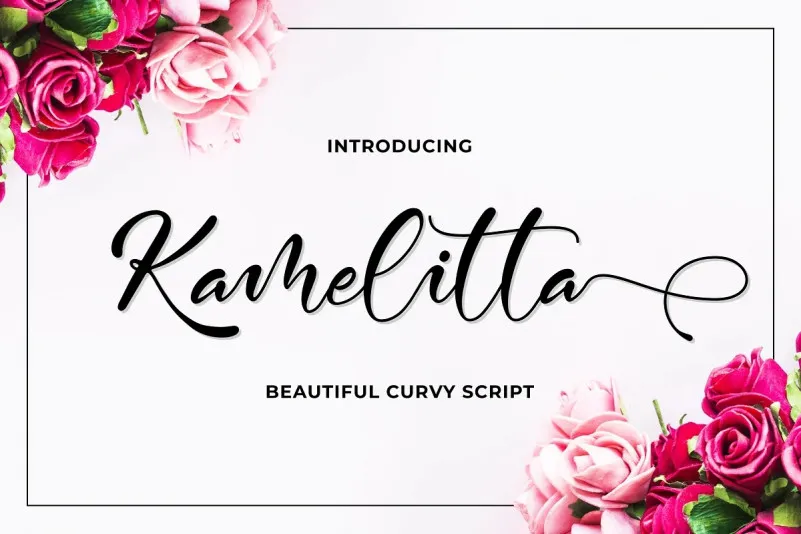
Kamelitta Font
Através do trabalho inovador realizado pela 99designs, apresentamos a Kamelitta Font, uma elegante tipografia círculo que irá enriquecer qualquer projeto de design. Esta font é um estilo script casual e encantador com swashes atraentes. Ideal para vários propósitos, como convites, logomarcas, capas de livros, artesanato ou qualquer outra necessidade criativa. A Kamelitta Font foi projetada especialmente para oferecer uma variedade impressionante de detalhes especializados, incluindo alternativas de letras e ligaturas. Ela também beneficia do PUA encoded, que lhe permite acessar facilmente todos os caracteres mágicos e swashes que desejávamos introduzir nesta font. A Kamelitta é uma opção perfeita para quem procura um estilo atraente, versátil e com alto impacto visual. Esta fonte não só oferece um toque elegante às suas criações, mas também garantirá uma experiência de design única. Adote já a Kamelitta Font na sua próxima empreitada gráfica e transforme seu trabalho de design no que nunca foi antes.